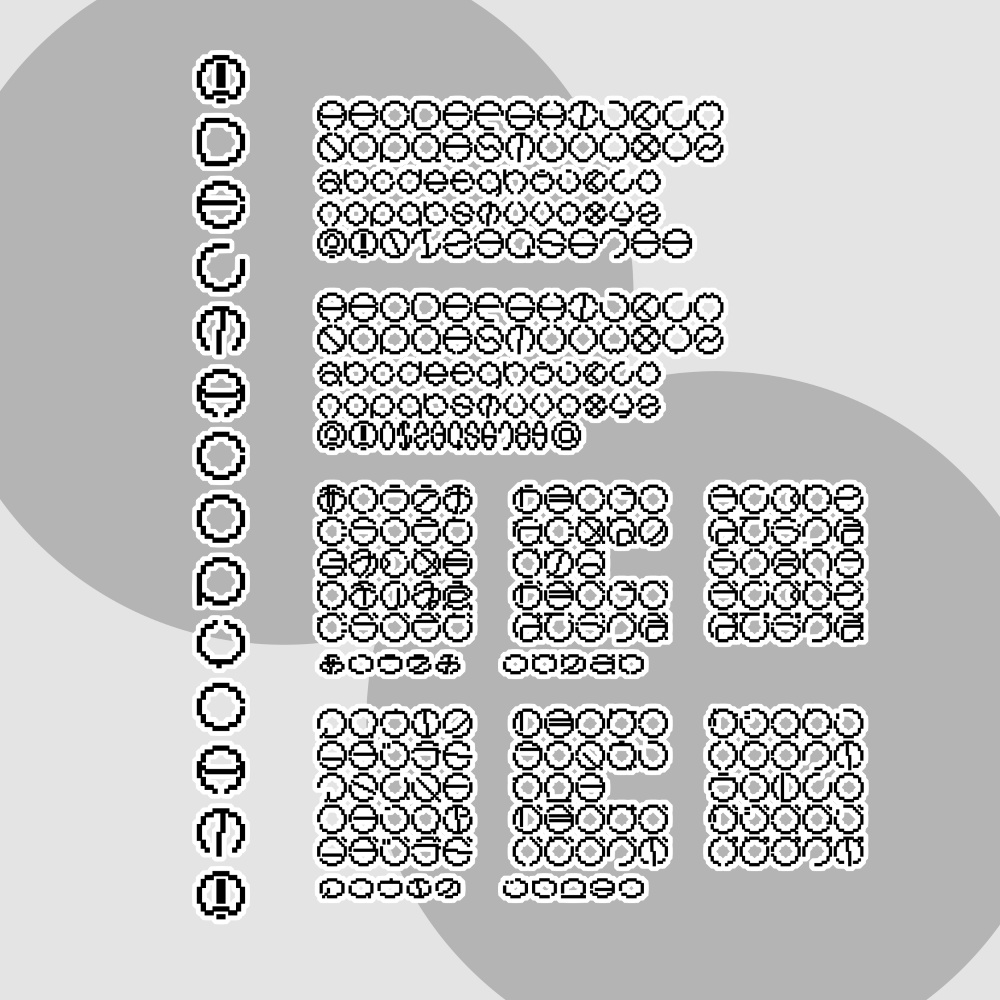
多忙のため事前に開けておきます。(〜R8.4.10まで配布予定) ______________________________ 毎年4/10&気が向いたとき&イベント時に配布しているフォントです。 ______________________________ 「DELTACOPYCAT(Qma-decopycat.ttf)」は フォント作成について何も知らない触手(加熱九真/shokushuQ)が https://www.pentacom.jp/pentacom/bitfontmaker2/ さんの力によって、手打ちしてつくったドットのフォントです。 何も知らないので横書きのことしか考えていません。 ■利用範囲 個人利用、商用利用、ウェブフォントやゲームなど独自性のあるコンテンツへの組み込みは自由です。 年齢制限が必要なコンテンツにもご使用頂けます。 ■禁止事項 犯罪行為や違法行為への使用、改変前のフォントファイルを単独で再配布することは禁止します。 商標登録など、第三者が本フォントを使用できなくなる行為は禁止します。 ■改変と再配布 収録文字の8割以上を改変し、本規約(readme.txt)を改変前フォントの規約として明記・同梱することで再配布可能です。 ■免責 本フォントの使用により生じた損害について、制作者(加熱九真/shokushuQ)は一切の責任を負いません。 ■その他 必須ではありませんが、使用の際にクレジット記載があると嬉しいです。 ■収録文字について 現在、アルファベットは全角・半角ともに同じデザインです。 全角と半角のピクセル数が2:1ではありません。 全角スペースはかなり中途半端な幅です(修正方法模索中) 半角スペースを1ピクセル分にしてあるので、それでうまく調整してください。 ■全角 1234567890 ABCDEFGHIJKLMNOPQRSTUVWXYZ abcdefghijklmnopqrstuvwxyz?! ■半角 0123456789 ABCDEFGHIJKLMNOPQRSTUVWXYZ abcdefghijklmnopqrstuvwxyz?!@ ■ひらがな あいうえお かきくけこ さしすせそ たちつてと なにぬねの はひふへほ まみむめも やゆよ らりるれろ わをんゐゑ がぎぐげご ざじずぜぞ だぢづでど ばびぶべぼ ぱぴぷぺぽ ぁぃぅぇぉ っゃゅょゎ ■カタカナ アイウエオ カキクケコ サシスセソ タチツテト ナニヌネノ ハヒフヘホ マミムメモ ヤユヨ ラリルレロ ワヲンイヱ ガギグゲゴ ザジズゼゾ ダヂヅデド バビブベボ パピプペポ ァィゥェォ ッャュョヮ 記号はもう少し入っている、かも。 ____________________________ 20250404、規約変更。